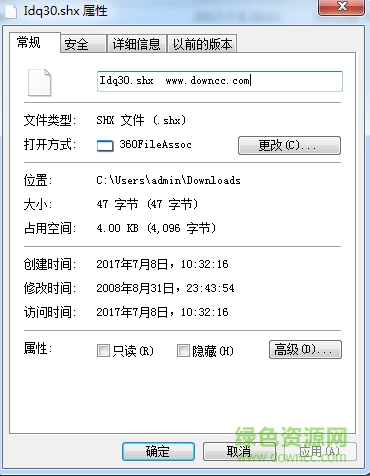
Idq30.shx字體官方免費版是一款大方好看的cad字體,字體線條簡練干凈,字形規(guī)范勻稱,設(shè)計效果出色,該字體兼容cad軟件以及其它制圖軟件,有需要者快來綠色資源網(wǎng)下載吧!
用shx字體做的文件相對會更小,顯示速度快,shx字體為線型字體,有線的屬性,可以更改線的厚度值,產(chǎn)生立體效果。